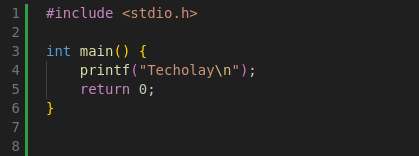
Merhabalar. Visual Studio Code'da sanki font görünümü biraz kötü gibi. Mesela Windows'da kullandığım zaman daha güzel ve net görünüyordu. Acaba font için ne yapabilirim? Fedora kullandığımı da belirtmek istiyorum. Yardımcı olacaklara teşekkür ediyorum.
Hesaba giriş yaptıysanız ayarları yedekleyip fontu kullanmayı deniyordur ama fallback vardir.
Hiç güzel bir çözüm değil ama komut satırı argümanı olarak ekleyip deneyin.
İlki ayarlarda da vardı diye hatırlıyorum. Unutmazsam bilgisayara geçince bakarım.
--disable-gpu --enable-use-zoom-for-dsf
Font değiştirmeyi de deneyebilirsiniz.
Aşağıdaki flag de is yapabilir.
--disable-lcd-text
Default font ile alakalı sanırım. Farklı font'lar biraz daha güzel görünüyor. Font weight ile alakalı da olabilir ama editör ince ayar yapmama çok izin vermiyor.
Evet, font kotu. Monaco'nun cok daha iyi gittigini dusunuyorum VS Code'da.
Köşelerde hafif bir bulanıklılık var hocam eğer fark ettiyseniz. Gerçi okunamayacak halde de değil ama rahatsız edici. Font rendering kötü galiba.